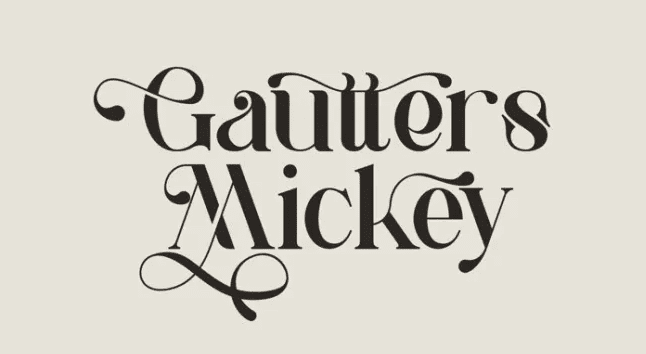
Название: Gautters Mickey Font (2021)
"Gautters Mickey" - уникальный современный шрифт с засечками. Поставляется с большим выбором альтернативных символов и лигатур.
Характерная форма каждого символа делает этот шрифт еще лучше для любого дизайна.
Создайте свой собственный уникальный дизайн с помощью этого шрифта. очень подходит для формального и неформального использования.
Доступен в двух стилях: обычный и курсив.